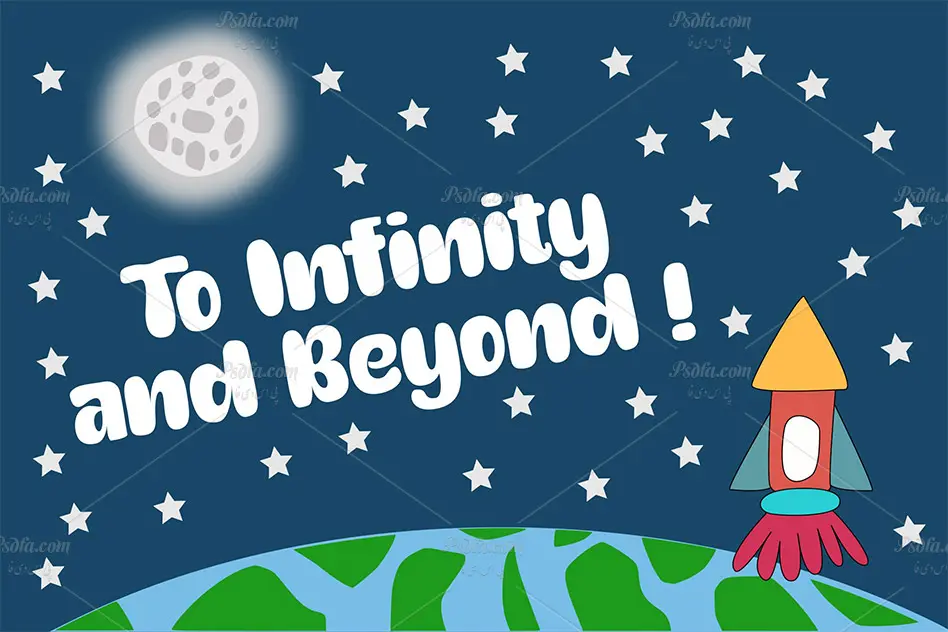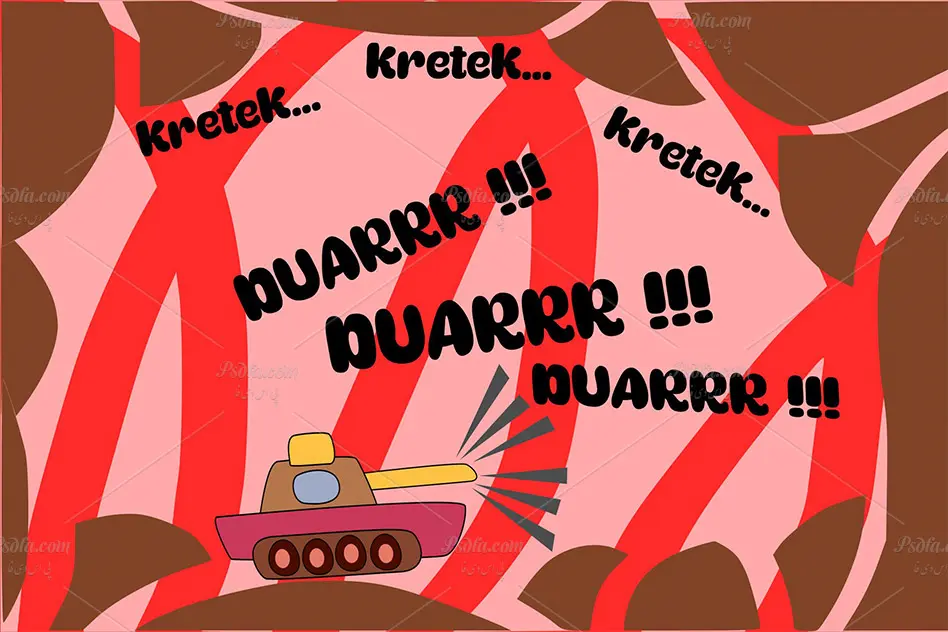
فونت انگلیسی کودکانه و فانتزی Little Merry با وزن ضخیم
در این مطلب شاهد فونت انگلیسی کودکانه و فانتزی Little Merry با وزن ضخیم مناسب جهت استفاده در عناوین طرح های گرافیکی می باشید. این فونت زیبا در قالب دو فایل otf , ttf بر روی سایت قرار گرفته است که با نصب این دو فایل در پوشه فونت های سیستم قادر به استفاده از آن در تمام نرم افزار های گرافیکی از جمله نرم افزار محبوب فتوشاپ ، افترافکت ، پریمیر ، مجموعه نرم افزار آفیس و … خواهید بود. فونت Little Merry در دو وزن معمولی (Regular) و ضخیم (Bold) طراحی شده است که می توانید از آن در طرح های گرافیکی خود به خصوص طرح های فانتزی و کودکانه همچون طراحی تقویم ، طراحی روی لوازم التحریر ، طراحی روی اسباب بازی و … استفاده کنید.